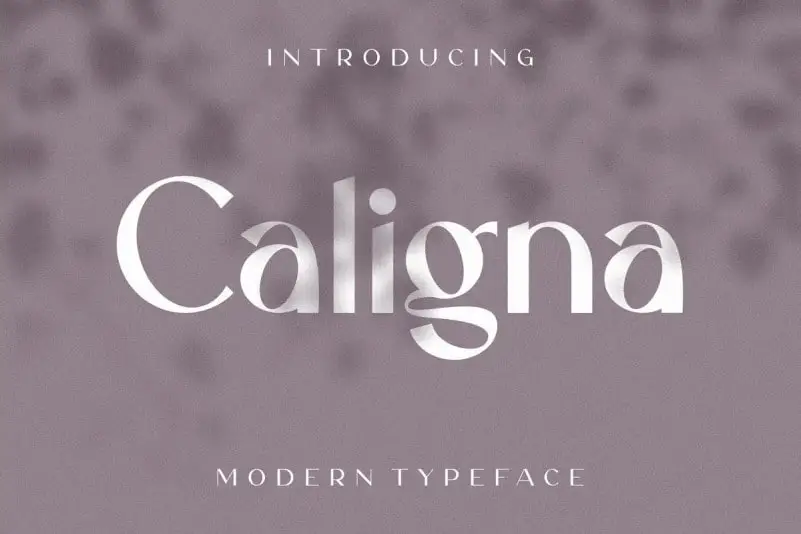
Caligna Sans Serif Font – Download Grátis
Caligna Sans Serif é uma elegante fonte sans-serif projetada para uso noturno em design editorial, embalagens, identidades corporativas e transmissões. Suas linhas sólidas e formas limpas a tornam perfeita para um projeto que precisa de uma aparência moderna e clara. Ideal para aplicar em logotipos, subtítulos de capa, rótulos de produtos e outros elementos visuais, Caligna Sans Serif traz um toque sofisticado à sua arte digital. Sua característica mais forte é a simplicidade que oferece uma sensação de conforto aos olhos do leitor. O designer 24Design Studios criou uma fonte com uma aparência luxuosa, perfeita para ambientes comerciais onde se encaixa bem em estilos como moda, gastronomia e hoteleira. O design de Caligna Sans Serif é ideal para designers que buscam um estilo atraente e moderno. Seja você um designer freelance ou profissional de uma empresa de branding, este fonte irá destacar seu trabalho ao dar aos seus projetos uma identidade visual única e envolvente. Sem dúvida, Caligna Sans Serif é o ótimo complemento para sua próxima criação grafica.